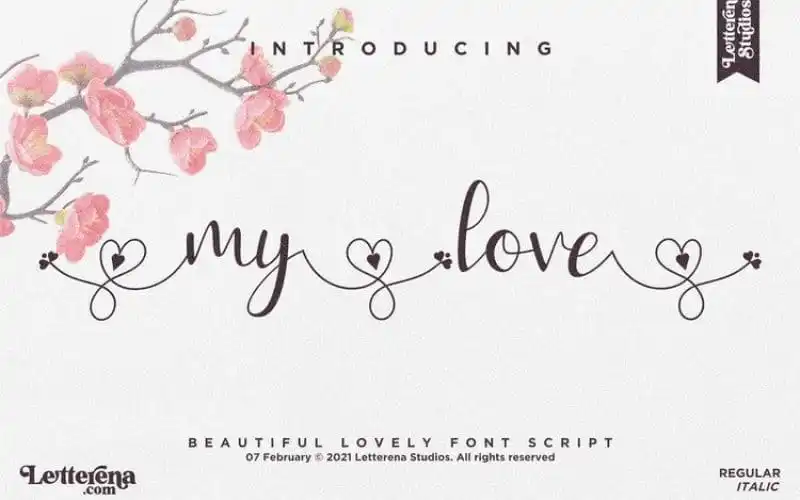
My Love Calligraphy Font – Download Grátis
A My Love Calligraphy Font é uma elegante fonte de calligrafia criada pela Letterena Studios, com um toque único que oferece uma experiência única e sofisticada para diversos projetos. Com sua rica variedade de letras, esta fonte atende a uma ampla gama de necessidades, incluindo logotipos, projetos de marca, designs de móveis de casa, embalagens de produtos, tigelas, citações, anúncios, sacolas de shopping, camisetas, capas de livros, cartões de nome, convites, cartões de felicitações, etiquetas, fotografia e até mesmo água-marinhas para eventos especiais. Esta fonte é ideal para aqueles que procuram um toque delicado e romântico em suas criações. Seja você um designer gráfico, ilustrador ou designer de moda, a My Love Calligraphy Font está aqui para trazer o charme da calligrafia à sua produção.